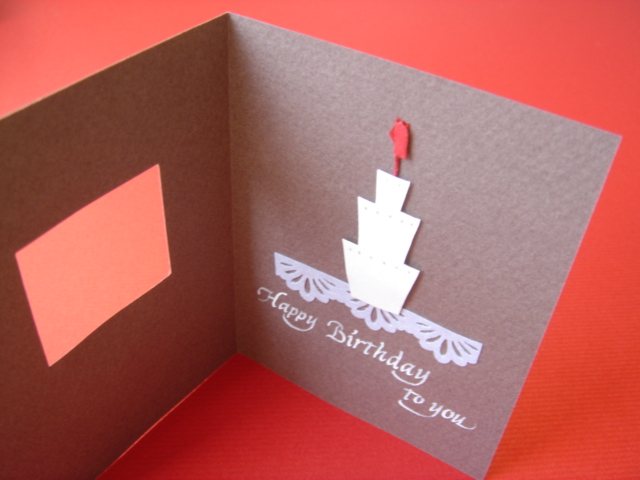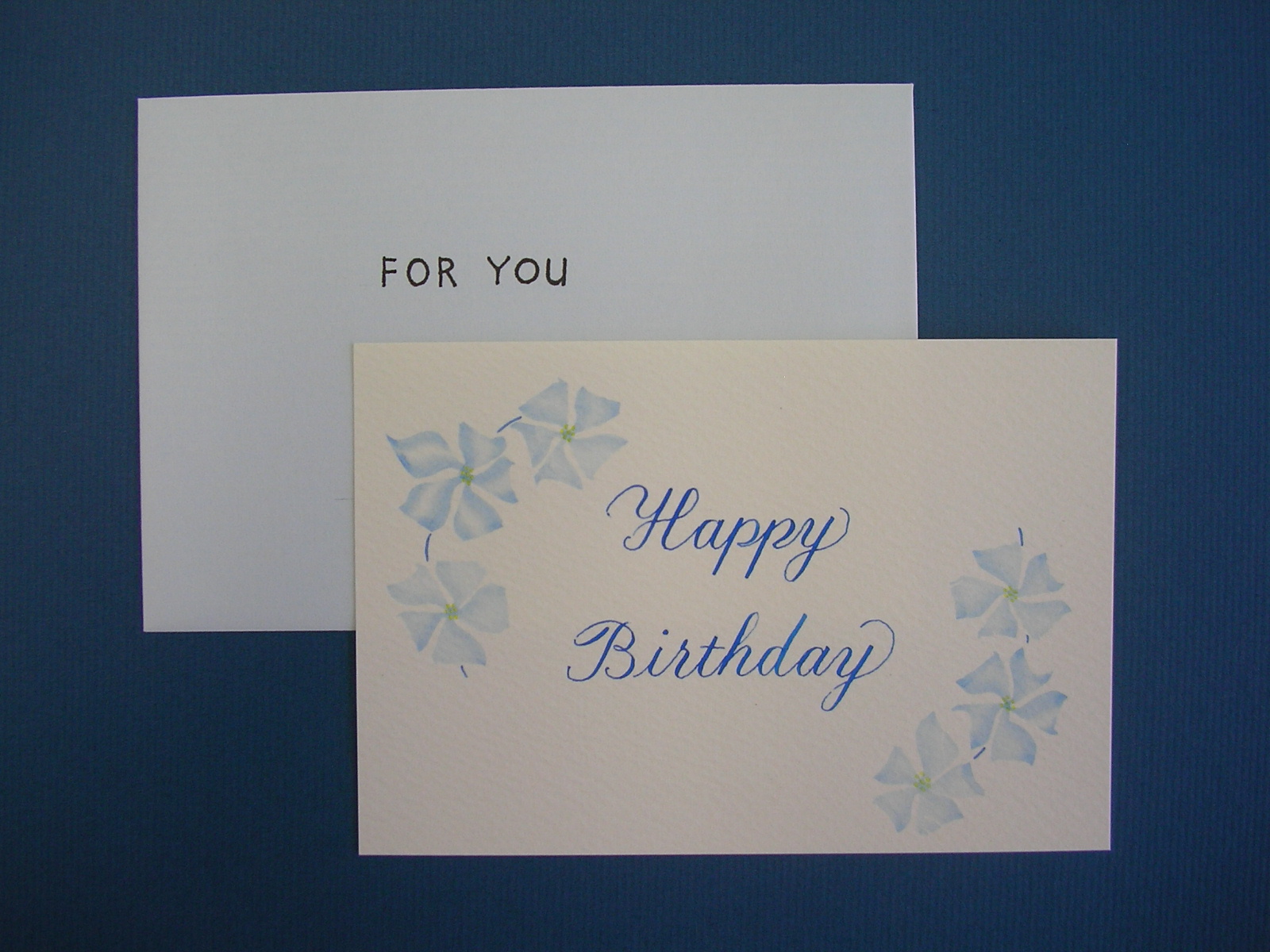
12月の誕生日カード
今月もモジトルエクスチェンジにはお誕生日を迎えた方がいらっしゃいます。
KHさん、AYさん、お誕生日おめでとうございます!
それではカードをご紹介!
まずはAAさんからKHさんあての誕生日カードです。
清楚な美しさですよね。カッパープレートが苦手、いえ、書けない私には憧れてしまうカードです。
平筆で描かれたお花(動きがきれい!)と文字が雰囲気がぴったり合って、やさしい印象です。
寒色系が、冬の凛とした空気を思わせますね。
こちらはSYさんからAYさんへの誕生日カードです。
手のひらに乗るくらいの小さめな美しい茶色のカード。
小窓から何かがのぞいています。なーに?
ひらくと、かわいい!お誕生日のケーキでした。立体感をもたせて
浮かせて貼ってあります。イタリックの文字も白でまとめてありシンプルな美しさ。
今月お誕生日のみなさまに・・・ハッピーバースデイ!